今天的教程是一个软中带硬,硬中带软的软广,因为我们又又又又出了一款新的字体,胡晓波觉得这款字体超级无敌好用,于是让我用这款字体出一个教程。
开始我就说了,这款字体过于漂亮,我的水平是不配用的,胡晓波说:“屁话少说,赶紧开始做。”
这年头,拍个马屁这门槛这么高吗?
我们先开始第一个案例了。
我们会经常发现文字太少很难排,几个文字放大缩小,上移下移,一下午过去了,ai的画板里的画面仿佛一切都没发生过。
太难了,做设计太难了。
其实要转化一下思路,文字本身是比较少,只要文字层级分好,画面的表现重点应该放在元素的刻画上,而不是单纯去编排文本。
当然了,这次教程是命题教程,我们先来看看我们的新字体。
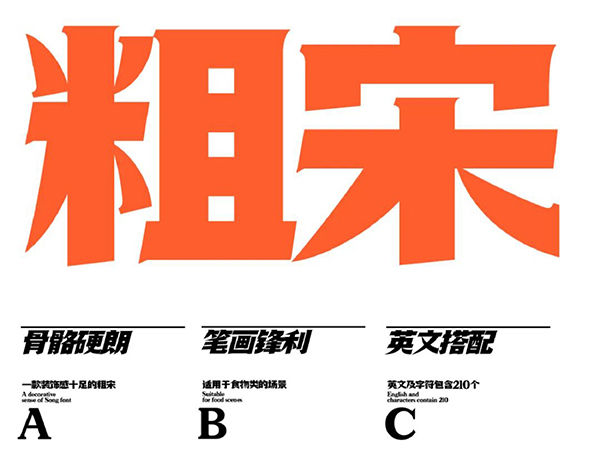
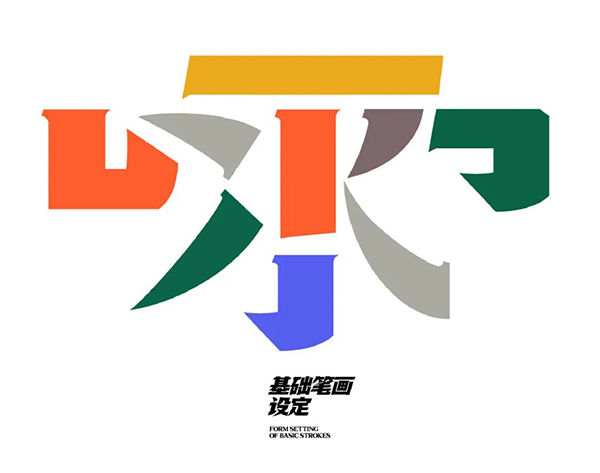
当然了,除了排海报,做文字logo那也是非常好用。
胡晓波看了都直呼内行。
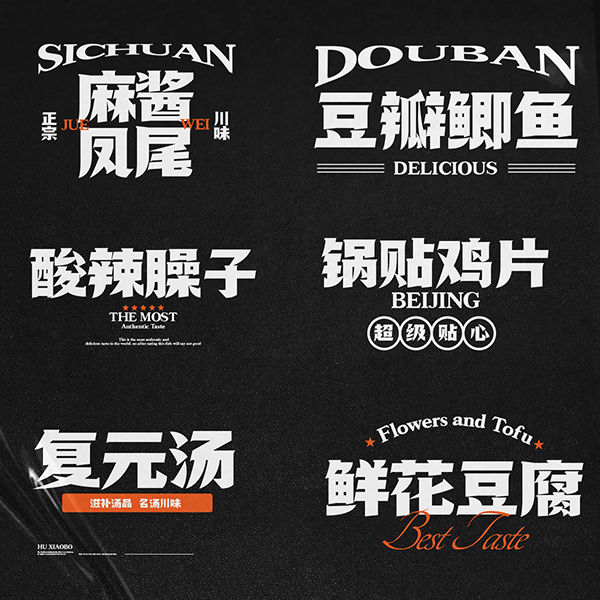
字体名字是“胡晓波香辣体”,这个名字不出意料就是胡晓波起的,简单直白没有文化,起个“胡晓波香喷喷体”不比香辣体强多了?
我怀疑胡晓波起这个名字还有另一层意思,以后就可以对外吹牛逼“大家以后听见胡晓波香辣体这个字体名字,就对胡晓波流下了深情的口水。“一个直男的幻想,就是这么可耻且肮脏”
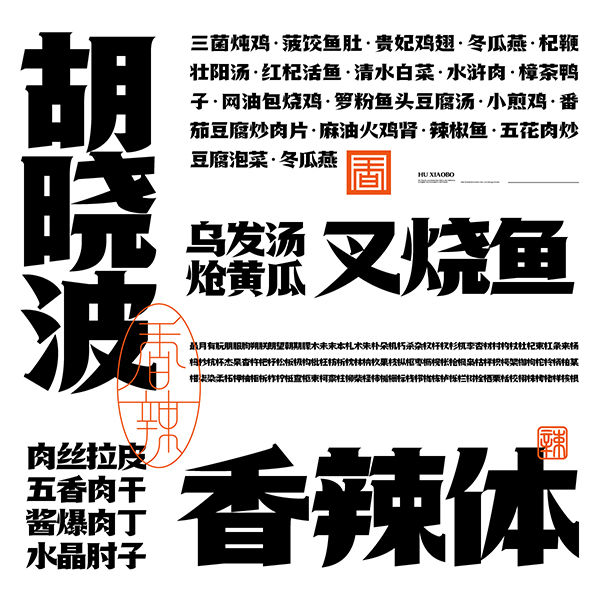
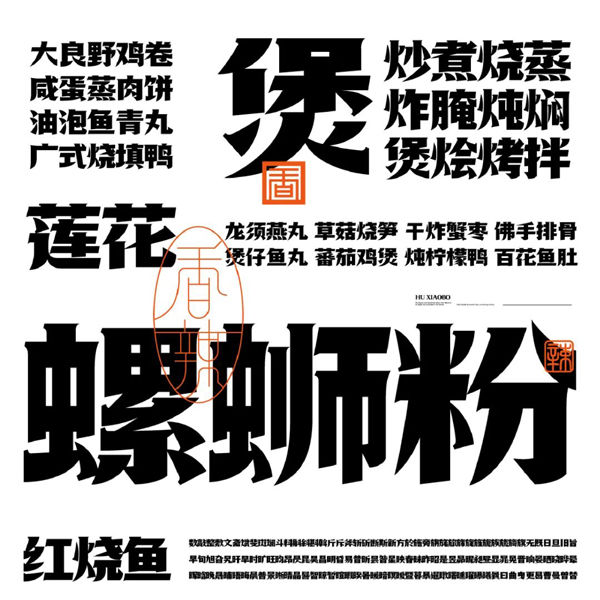
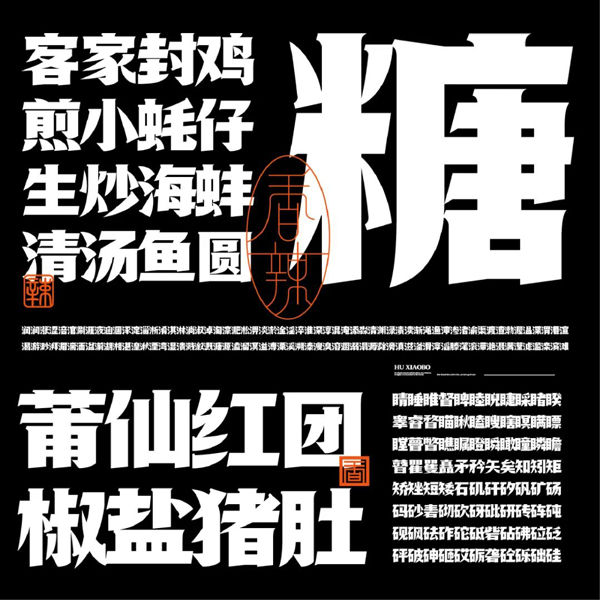
好了,大家对这个字体有一个简单的了解后,我们要使用这个字体来做案例了。
第一个案例,我们做一个杯子的海报。
首先对于杯子有个简单的摆放,有个简单的远近关系。这样比直接放置会有一个空间层次关系。
然后我们可以设定一个简单的外框,目的是让画面变得更加有整体关系,元素不会显得零散。
然后细化一下这个框的一个细节关系,让这个框的细节感更多一下。
可以先加一个背景纹理,加一个简单的放射线。
我经常看见有同学错误使用放射线,一般注意作为背景纹理的话,颜色只需要加深一点点,跟其他的颜色有一个简单区分就可以了。
接下来这一步就非常非常关键了,我们要开始排列文字了,我们选择“胡晓波香辣体”,作为主题,相应再去加一些文字效果。
再加个简单的标签,跟外框有一个简单的融合关系。
好了,我们接下来将所有元素与文字整合一下,看看画面的最终效果。
总结一下第一个案例中用到的方法。
接下来我们看一下第二个案例。
题目还是原来的题目,不是因为我懒,只是因为我做完第一个案例后,觉得色彩使用的有些保守了。
这一版本我想使用一个更清新一点的色彩。
当然了,你还是要再看一眼这个杯子,为什么?
因为文章篇幅不够,重复来凑。
这次我们先确定背景及色彩,为了表现杯子的属性。我想加一些流动的曲线,简单做一个背景出来。
然后加产品进去。
这里我简单添加一个投影,这种版面的风格不适合加虚化的投影,,加一个简单的色块即可。
又到重头戏了,那就是排列标题,这里我使用一个中英文的一个简单叠加效果,增加画面层次。
色彩选择红配绿和白色。
为了表现画面的趣味感,这里我仍然加一个标签,将信息放置标签中是一个非常好用的做法,聚焦信息,增加视觉冲击力。
总结一下第二个案例中用到的方法。
接下来我要换一个题目了。
是不是很感动?胡晓波都快哭了,教程太良心了。哭着哭着就要扣我工资...
第三个案例我们排一个钥匙扣。
这个案例并不好做,因为钥匙扣本身是比较零散的,排到一个画面当中很容易会显得松散,不够聚拢,所以第一步我们就要先解决一下这个问题。
创建面积感。也就是把钥匙扣放进一个形状当中。
这样的话,产品就不会显得特别零散。
接下来我们需要画一个外框,有同学就说了,怎么动不动就要画外框?
我是手残啊!这不欺负手残吗?
不,我是拯救手残。这一步我们用到的方法就是“就地取材”,我们看到产品上就有一个外框,我们直接拿这个外框的形式变化就可以,这样整个画面也具有一定的统一性。
这样我们就很容易就解决了画面的外框问题。
放置标题,给标题做一个简单的字体效果。
和画面的色彩形成统一关系。这样这个画面就完成了。
总结一下第三个案例中用到的方法。
接下来我们看一下第四个案例。
兜兜转转,我们又要做杯子了...
这是天意,要接受...
首先我们又要先看一下这个杯子了。
换了一个形状,是不是很感动?胡晓波都快哭了,教程太良心了。哭着哭着就要扣我工资...
似曾相识的一幕...
首先,因为是两个,其实画面我们一开始想清楚要怎么排,画面划分成两块就可以。
然后给背景和画面中的两个色彩分别加背景图案,细节刻画的丰富一下。
我们把杯子分别放置进去,倒也不必非得正着放置,有时候加一点角度显得俏皮一点也更适合这个杯子的画面主题。